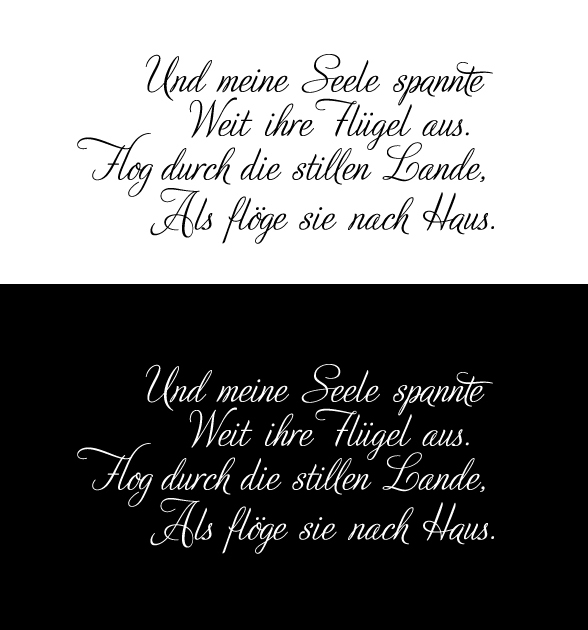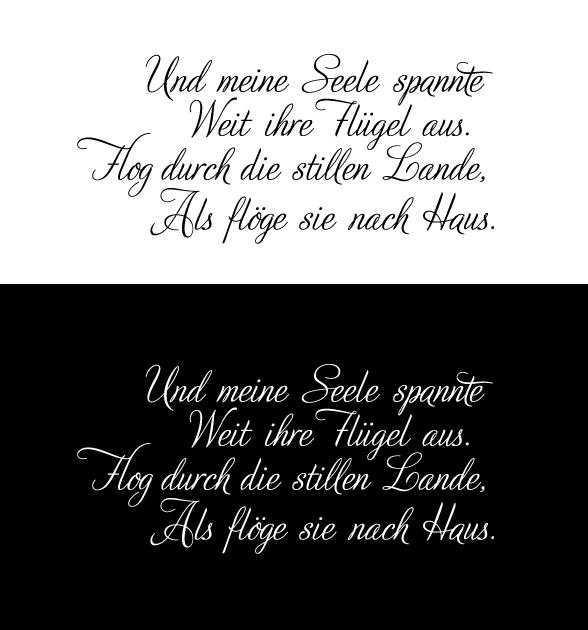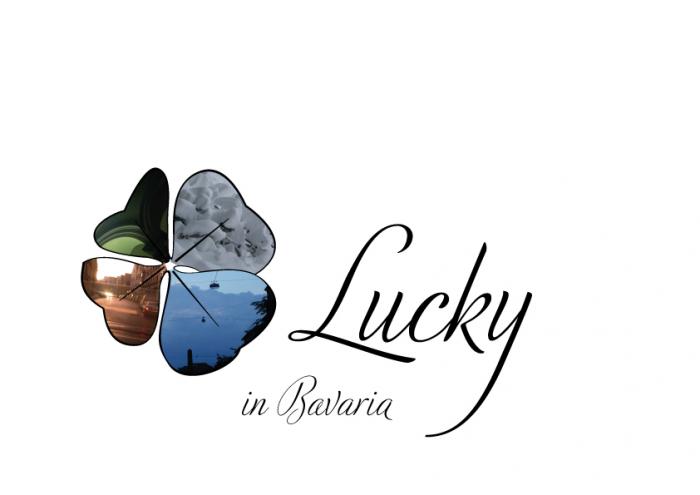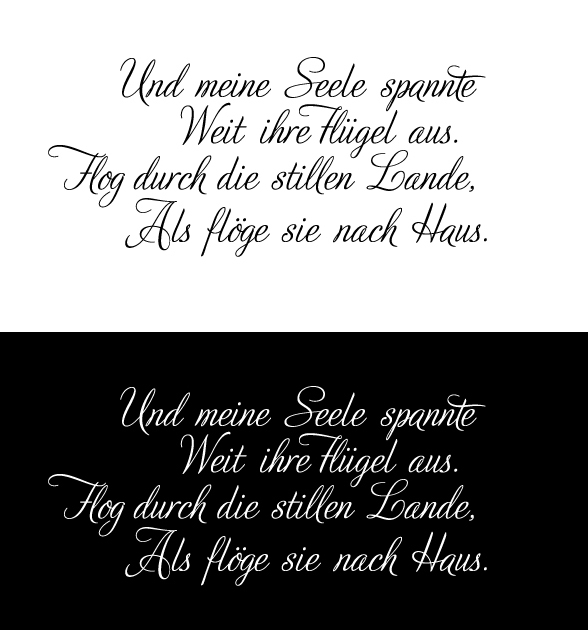
Spationieren von Adios Script Pro
Zum Thema „Handschriftähnliche Umsetzung einer verbunden geschriebenen Schrift“ habe ich eine Lösung aus einer andedren Welt gefunden, die man vielleicht ja auch auf die lateinischen Schreibschriften übertragen könnte.
Der Word-Shaper des InDesign-Plugins Tasmeem für arabische Schrift baut den Text nicht aus ganzen Buchstaben zusammen, sondern verwendet Primitives, welche es in 2 Dimensionen zum durchgeschriebenen Wort zusammenfügt, und dabei, um die Zeile ordentlich auszutreiben alle nur erdenklichen Formalternativen quasi automatisch durchspielt. Dabei entstehen je nach Wortlänge hunderte Alternativformen, von denen viele sehr handgerschrieben wirken. Hiermit bietet sich auch die Möglichkeit, anders als in der üblichen Druckschrift dieses Schriftsystems nicht an der Grundlinie zu kleben.
Guten Morgen zusammen, danke für die Antworten. Ich mag das arabische Beispiel. Ich werde das gleich mal beim Vektorprogramm ausprobieren was gesagt wurde. Ich werde den Freund meiner Schwester (für Ihn ist das Tattoo) fragen, ob er den Aufwand eines Kalligrafen eingehen will und ich werde ihn auch befragen ob der Tätowierer Erfahrung mit Schriften hat. Ihr habt natürlich recht, wenn man dem Typo Gesetz "Angemessenheit" hier gerecht werden will, sollte ein möglichst hoher Aufwand betrieben werden. (Der Körper ist ja kein "billiger" H&M Prospekt der dann nach einer Woche weggeworfen wird).
p.s.: Anbei der Anhang mit aufgestelltem f, aber sonst die Oberlängen unberührt gelassen. Stattdessen Wortabstand nocheinmal verkleinert damit gilt Wortabstand<Zeilenabstand. Ich denke, sollte er nicht zum Kalligrafen gehen, werde ich es so belassen, außer von Ech entdeckt wer noch n gravierenden Fehler!
Bei dem speziellen F bei „ihre Flügel“ probiere doch mal aus, das ganz ohne Wortzwischenraum zu schreiben, denn den bringt diese spezielle Buchstabe fast schon von Haus aus mit, bestenfalls ein ganz schmales Leerzeichen.
Ok, habe an den beiden großen "F" Buchstaben gearbeitet. Was mir noch aufgefallen ist, die vierte Zeile hat einen zu großen Zeilenabstand, verkleinern kann ich Ihn aber nicht wegen der Oberlänge von A und H. Oder geht das durch? Sonst noch irgendwelche Mängel? Ich finde "Flog" sieht nun nicht mehr nach Aog aus und "Flügel" ist nicht mehr ganz so schlimm.
Die Wortzwischenräume sind immer noch zu weit, außer »ihre Flügel«, der ist jetzt enger als alle anderen. Sie sind auch nicht gleichmäßig, »Seele spannte« steht weiter als »Flog durch«, beispielsweise. Der letzte Durchschuß ist in der Tat zu groß, das Versal A hängt nach unten, während das F von Flügel zu hoch steht. Das F ist insgesamt nicht besser geworden, es ist eher ein J oder ein T als ein F. Die Schrift taugt nicht viel, das kann man nicht reparieren. Es sieht wegen der Schrift bieder aus, es sieht dazu schlecht gesetzt und dadurch als Ganzes billig aus.
Kalligraf oder Schriftwechsel, mit dieser Type kommst du nicht zu einem guten Ergebnis.
Das ›Flog-F‹ finde ich gar nicht so daneben – die Schrift auch nicht. Ein J und T sehe ich da schon gar nicht drin ...
Im Prinzip wird man an jeder Satzschrift herumkrittle können und selbst an Kalligrafien findet das geschulte Auge immer etwas was nicht stimmt und ›schlecht‹ gemacht ist. Die Kunst ist es sich zu entscheiden, welche ›Macken‹ man hinnimmt und welche man ausbügelt – das macht die ganze Sache individuell und lebendig
Mit gefällt das A allerdings nicht so richtig, das finde ich am schwersten zu erkennen. Dass es tiefer hängt sehe ich nicht als Problem. Dass das F etwas schwebt eher. Da könnte man einfach den Schwung etwas tiefer ziehen.
Dass die letzte Zeile den Anschluss verliert, liegt daran, dass eine ganze Strecke lang keine Oberlängen vorkommen, das reißt eine Lücke und hat nichts (soweit der Zeilenabstand überall gleich eingestellt ist) mit dem Durchschuss zu tun. Wenn du den verringerst kriegst du nicht nur Probleme mit dem A, sondern es kann dann auch wieder falsch und unregelmäßig wirken. Ich würde jetzt eher gucken, ob man den Raum nicht anders füllen kann. Z. B. eins der ›stillen-l‹ etwas nach unten ziehen oder die Schlaufe des L von Lande  nutzen. Vielleicht braucht es da auch gar nicht viel Veränderung, also die Fläche muss nicht gänzlich gefüllt werden, es reicht, wenn sie nicht mehr ganz so riesig wirkt.
Meine Vorgehensweise wäre jetzt (da der Tätowierer eh keine digitale Vorlage braucht) das Ganze ausdrucken, abpausen und dabei diese Schwünge und Schlaufen anpassen. Das geht manchmal schneller als wenn man jetzt die einzelnen Ankerpunkte der Pfade anfässt. Dabei würde ich evtl. auch den ersten t-Strich von der Idee her um 180° drehen.
Ob du dir so eine manuelle Bearbeitung zutraust steht natürlich auf einem anderen Blatt ...
@Martin Z. Schröder, Der Beitrag erinnert mich stark an meinen Schrift Lehrer. Er hat auch immer versucht mir die "Flausen aus dem Kopf zu treiben" und ich wollte immer lieber zeichnen und fotografieren. Danke für den guten Willen an dieser Stelle.
Ich nochmal, entschuldigung für den Doppelpost, wollte nur anhand von einem Beispiel das ich mal so schnell gefertigt habe sagen, dass die Adios Script Pro eine schöne Schrift ist und auch für fröhliche Dinge verwendet werden kann. :p